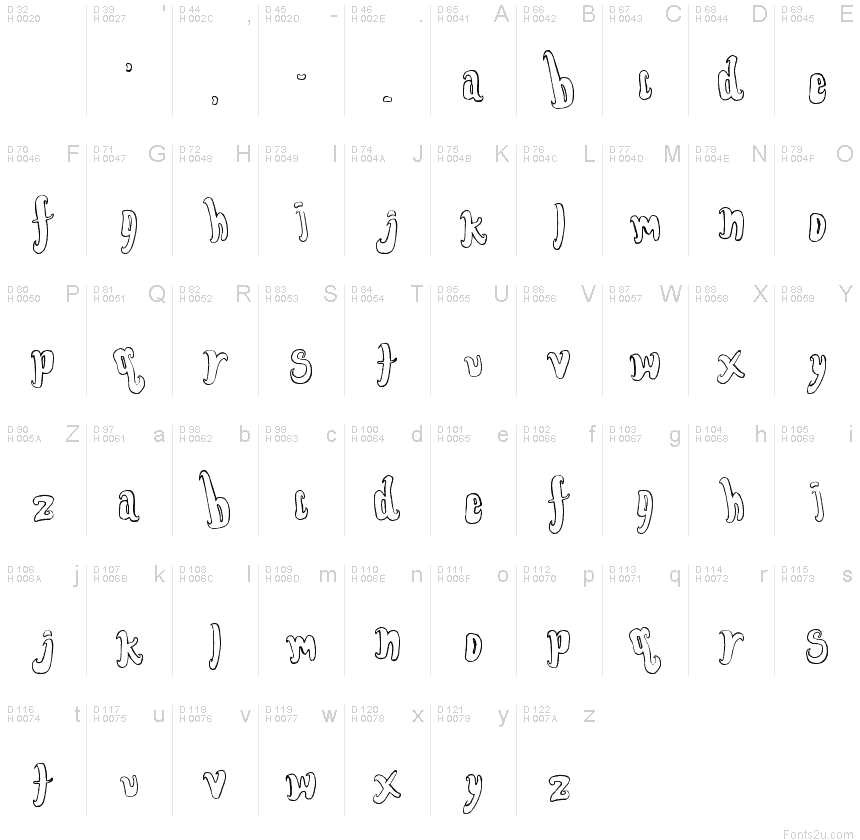
Font For The Dumped Outline od Jasona Fagone to darmowy, komiksowy font typu display, który wygląda, jakby został nabazgrany na marginesach listu o zerwaniu. Litery chwieją się, rozciągają i nachylają ku sobie, z luźnymi, atramentowymi konturami, które wydają się surowe i lekko szalone – jakby powstały w jednym, gorączkowym zrywie. Ta szkicowa, nierówna linia nadaje każdemu słowu nerwową energię, trudną do podrobienia przy użyciu bardziej sterylnych, cyfrowych stylów.
Używając Font For The Dumped Outline, możesz nadać swoim zinom, okładkom niezależnych albumów, plakatom o rozstaniu, kartkom anty-walentynkowym, komiksom czy grafikom do mediów społecznościowych katartyczny, ręcznie robiony sznyt. Ten darmowy font najlepiej prezentuje się w dużym rozmiarze, gdy pozwalasz jego konturom „odetchnąć”. Zestaw go z prostym krojem bezszeryfowym (groteskiem lub geometrikiem) w nagłówkach i szczegółach, aby chaos pozostał czarujący, a nie przytłaczający.